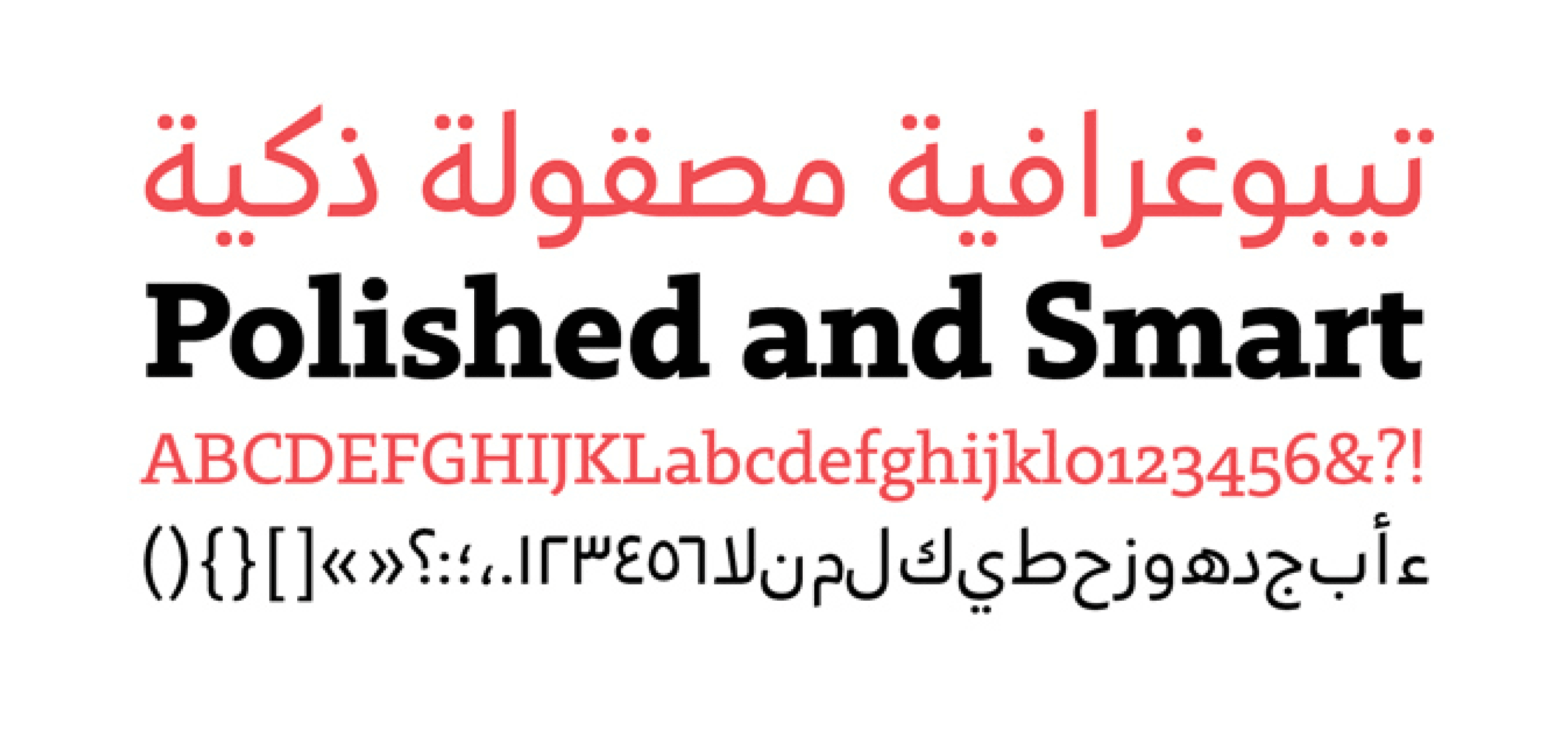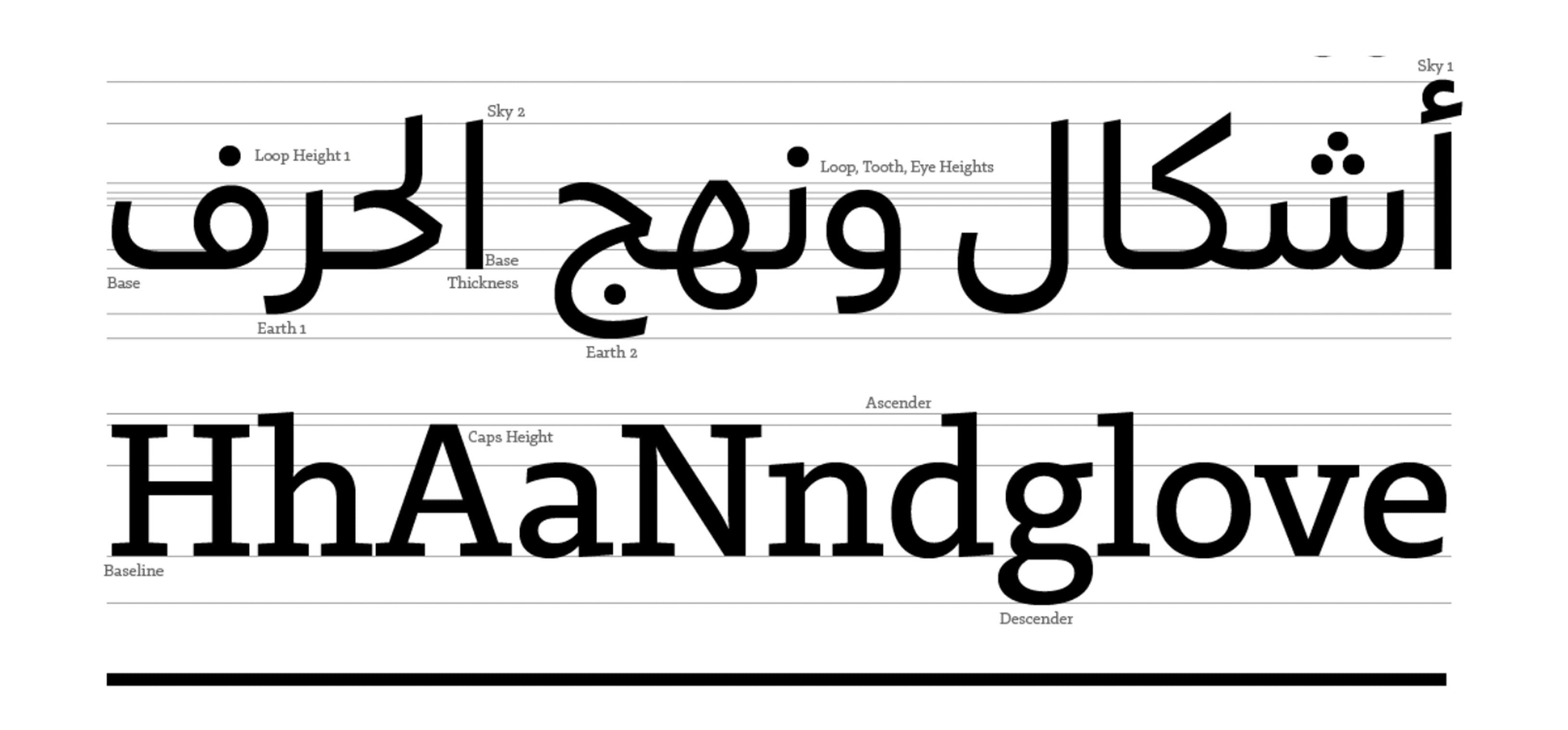
يمثل 29LT Zarid Slab امتدادًا قويًا لعائلة زرد، حيث يجمع بين التصميم الطباعي الصارم والمظهر العصري الجريء. يتميز بوجود نهايات مربعة (Slab Serifs) تضيف ثباتًا بصريًا وهيبة على العناوين والنصوص التحريرية.